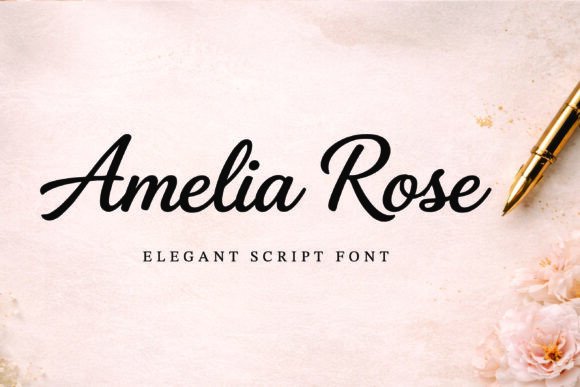
Amelia Rose
適切なデザイン要素を見つけるのは難しい場合がありますが、Amelia Roseは作品を即座に引き立てる優れたコレクションを提供します。
POD(オンデマンド印刷)製品、結婚式の招待状、またはソーシャルメディアのグラフィックを作成している場合でも、Amelia Roseは理想的です。